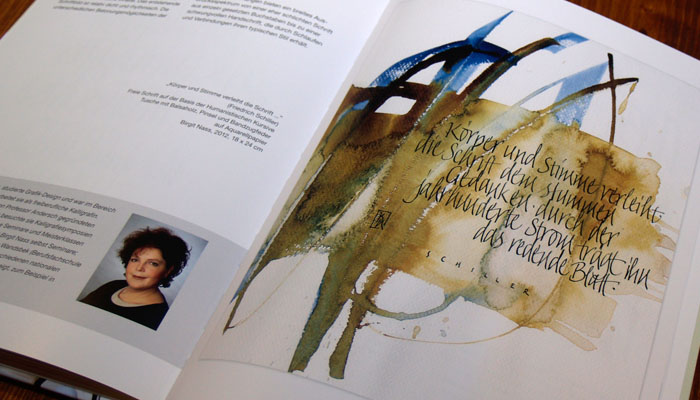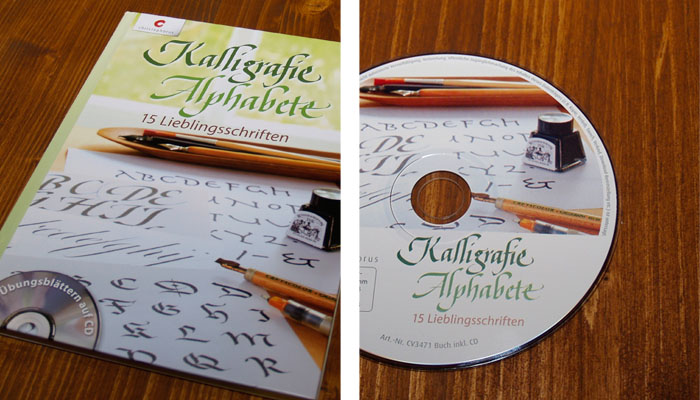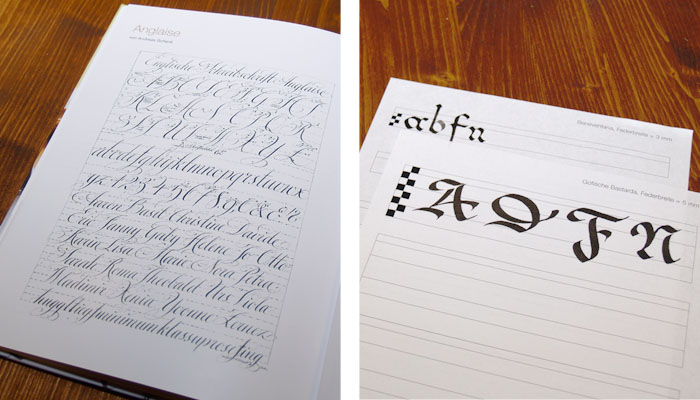
»Die Auseinandersetzung mit den klassischen Schriften gehört zu den Grundlagen der Kalligrafie und ist in vielerlei Hinsicht hilfreich. Anfängern vermittelt das Erlernen eines Alphabets das Gefühl für Formen und Proportionen einer Schrift und schult den Blick für Qualität. Für geübte Kalligrafen ist die immer wieder neue Interpretation bekannter Schriften sehr reizvoll und spannend. Außerdem hilft das Studium des formalen Charakters der verschiedenen Schriften bei der Entwicklung eigener Alphabete. In diesem Buch stellen elf erfahrene Kalligrafinnen und Kalligrafen klassische Schriften, wie Römische Kapitalis, Rustika, Karolingische Minuskel, Merowingisch und Beneventana, sowie freie Alphabete vor. Zu jeder Schrift werden die Besonderheiten erklärt. Außerdem zeigt jeder Kalligraf eine Arbeit in 'seiner' Schrift. Hier wird das breite Spektrum kalligrafischer Ausdrucksformen deutlich. Die verschiedenen Ansätze ermutigen zum Üben, denn sie zeigen, dass sich die Mühe lohnt, und bieten Anregungen für eigene Gestaltungen.« (Klappentext)
Die 15 Alphabete werden in der Regel auf zwei Doppelseiten dargestellt – jeweils mit einem Musteralphabet, teilweise einem Beispielsatz und einer Arbeitsprobe mit der entsprechenden Schrift des jeweiligen Kalligrafen. Die Künstler selber werden mit einer kurzen Vita und und einem Bild vorgestellt. Auf der beiliegenden CD sind 53 PDFs mit linierten Übungsblättern zum Ausdrucken enthalten.
Das Buch bietet eine interessanten Einblick in die derzeitige Kalligrafie-Szene, denn es sind im Wesentlichen fast alle namhaften, aktiven, deutschen Schriftkünstler vertreten. Man lernt sie ein wenig über ihre Kurz-Vita, die Wahl ihres Lieblingsalphabets und die Arbeitsproben kennen. Das ist alles ganz interessant, zumal man eben die verschiedene Stile hier direkt nebeneinander sieht. So findet der geneigte Einsteiger auch eine Orientierung über die Bandbreite dessen, was möglich ist.
Auch wenn man es vom »Christophorus Verlag« gewohnt ist und die CD mit den Übungsblättern den Anschein erweckt, dass es sich hierbei um ein klassisches Buch zum Erlernen der Alphabete handelt, ist dies nicht unbedingt der Fall. Dafür sind die Anleitungen und Erläuterungen zu den einzelnen Schriften einfach viel zu knapp. Deswegen weiß man nicht so richtig, wofür dieses Buch gedacht ist. Als kleiner Einblick in das derzeitige, hiesige Kalligrafieschaffen ist es kurz und bündig, aber, auch für den Preis, durchaus in Ordnung. Durch die Aufbereitung mit Übungsblättern wirkt es, als wolle man damit eine breitere Käuferschicht ansprechen – allerdings könnten viele auch enttäuscht davon sein.